Материал обновлен в ноябре 2021 года. Шрифт для презентации может сделать текст читабельным и выразительным, поможет эффектно подать важные мысли и идеи. Опытные дизайнеры умеют грамотно оформить каждый слайд, но новички могут запутаться в многообразии шрифтов для презентации и выбрать нечитабельный или неуместный вариант. Команда Canva собрала лучшие шрифты для презентации для 2021 года: от универсальных и сдержанных до технологичных и ультрамодных.
1. Montserrat
Montserrat — минималистичный и приземистый шрифт для презентации, который отлично читается в обычном начертании и хорошо смотрится в заголовках в полужирном варианте. Подходит для материалов, где нужно передать теплую и дружелюбную атмосферу, но при этом сохранить деловой тон. Такие шрифты для презентации ассоциируются с темами здоровья, фермерства и ресторанного бизнеса.
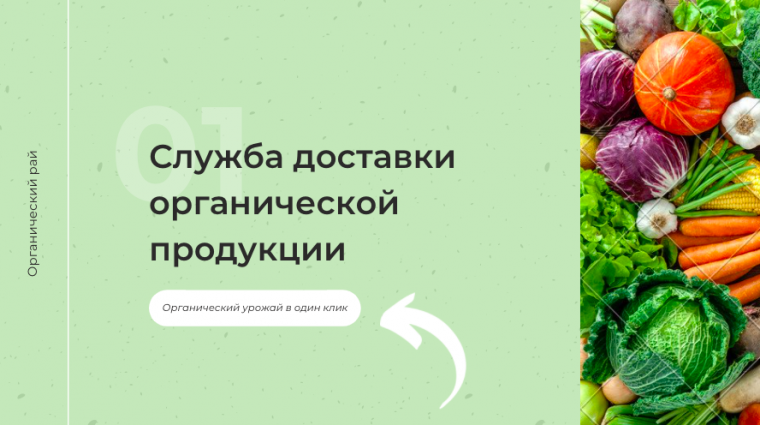
2. Tenor Sans
Еще один шрифт для презентации с очень теплым и доверительным настроением. Его могут смело выбирать начинающие предприниматели, которые не стремятся к большим масштабам, а хотят создать небольшое семейное производство с особым вниманием к деталям. Шрифт для презентации Tenor Sans вызывает ассоциации с семейными рецептами, русскими традициями и ручным производством.
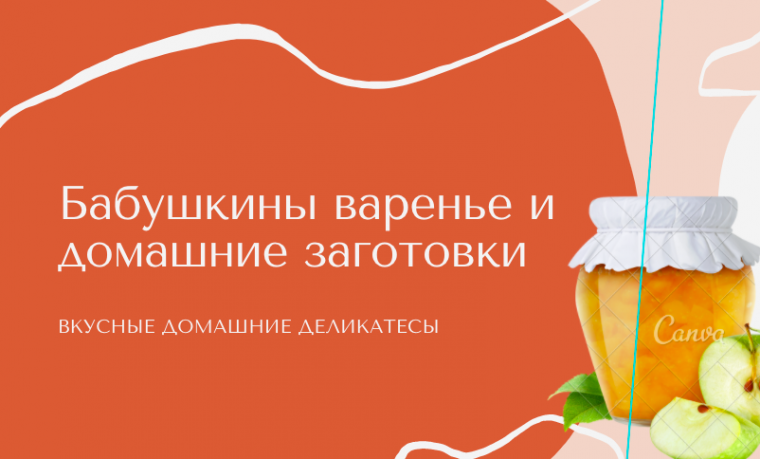
3. HK Grotesk Medium
Этот шрифт для презентации лучше всего смотрится на экране компьютера или планшета. Он хорошо читается за счет простой формы и отсутствия засечек, но при этом выглядит интересно и привлекает внимание. Главное, следить за тем, чтобы шрифт для презентации был нужного размера. HK Grotesk Medium отлично подойдет для материалов инновационных интернет-сервисов и стартапов.
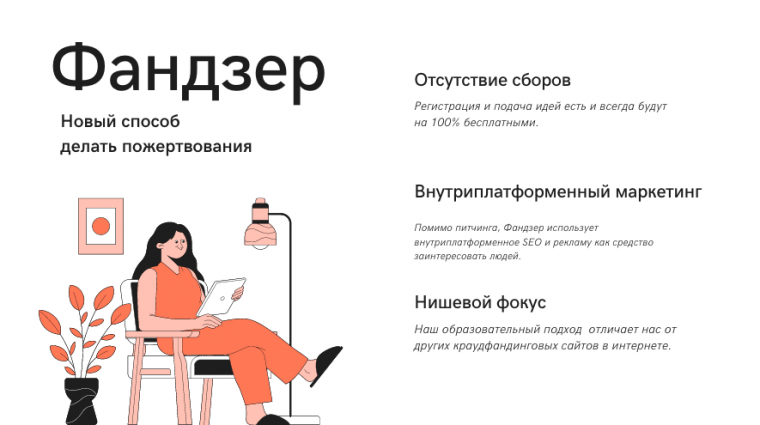
4. Geometria
Geometria — популярный шрифт для презентации, который хорошо знаком даже новичкам. Пропорциональные буквы, простая форма и несколько вариантов начертания позволяют создать читабельные слайды, которые выглядят представительно и сдержанно. Это отличный шрифт для деловой презентации компании.
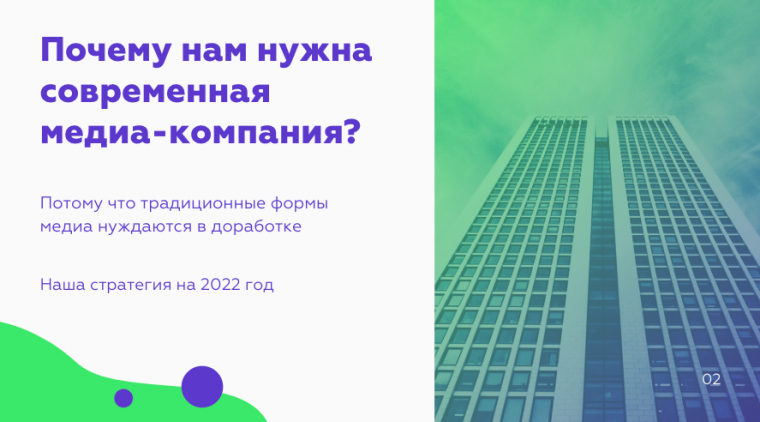
5. Open Sans
Лучшие шрифты для презентации для 2021 года невозможно представить без Open Sans, который занимает ведущее место среди шрифтов для веб-дизайна. Его по умолчанию используют многие интернет-сервисы и приложения. Он универсален и подходит для презентаций на любую тему.
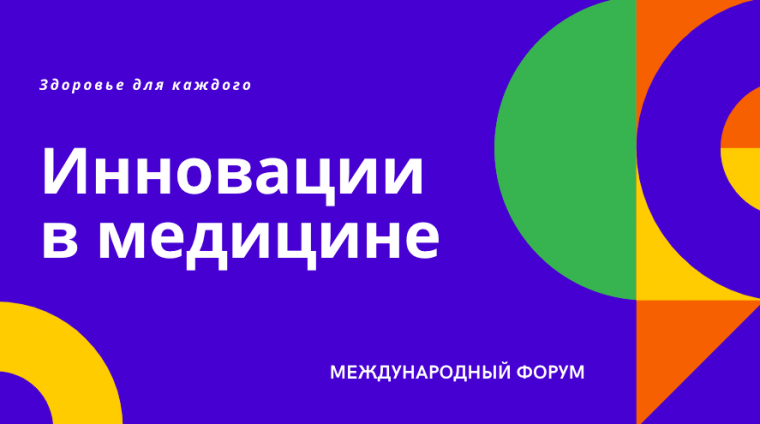
6. Roboto Condensed
Roboto — отличный шрифт для презентации, потому что компания Google разработала его специально для операционной системы Android. По этой причине он отлично смотрится, как на мобильных устройствах, так и на других экранах и проекторах.
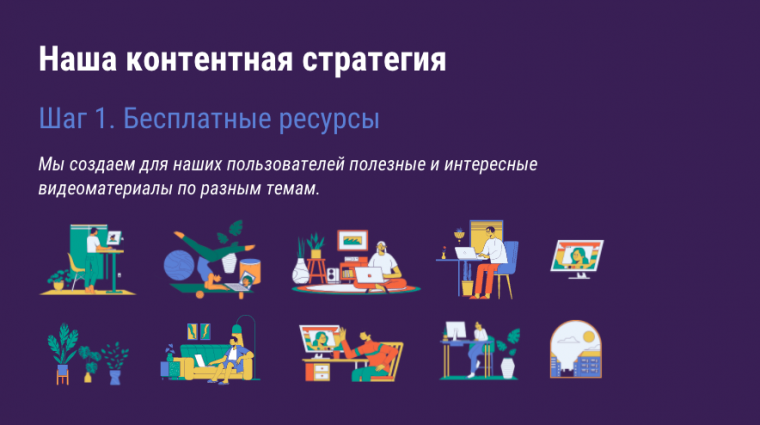
7. Clear Sans Regular
Еще один шрифт для презентации, который отлично читается на любом экране. Clear Sans Regular выглядит представительно и модно одновременно. С его помощью можно удачно оформить материалы, связанные с миром музыки и интернет-сервисами, также он хорошо подойдет для медиа.
8. Fira Sans
Технократичный и ультрасовременный шрифт для презентации Fira Sans лучше всего смотрится на контрастном фоне и хорошо сочетается с кислотными цветами, которые сейчас в моде и ассоциируются с бурным развитием интернет-сервисов. Попробуйте этот шаблон, если готовите материал для интернет-проекта.
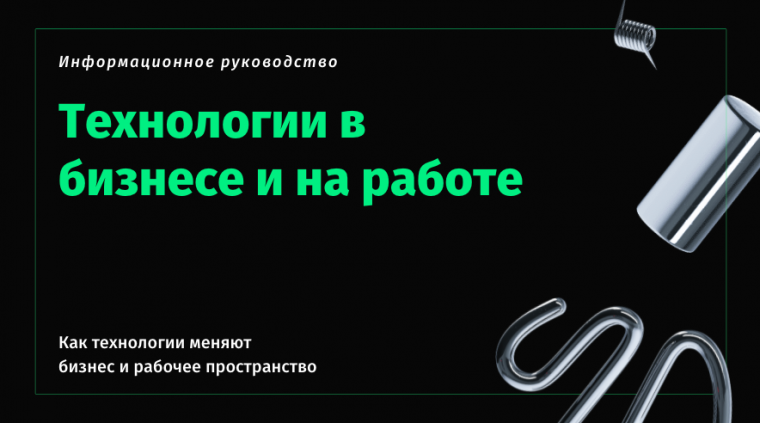
9. Prosto
Еще один отличный шрифт для презентации на тему интернет-технологий. Буквы отличаются открытыми, плавными чертами, а в некоторых из них скругления выполнены оригинальным образом. Отличный шрифт для презентации, если вы хотите выглядеть технологично и современно.
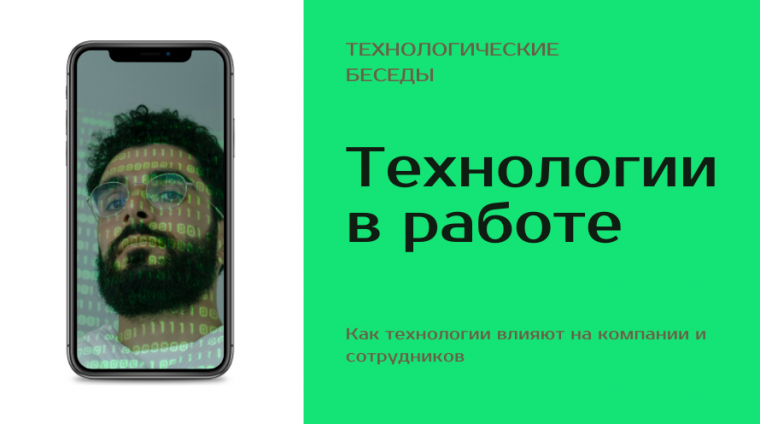
10. Inter
Inter — шрифт для презентации с насыщенными буквами без засечек.
- Отлично подходит для заголовков или оформления объемных текстовых фрагментов;
- хорошо смотрится на контрастном фоне.
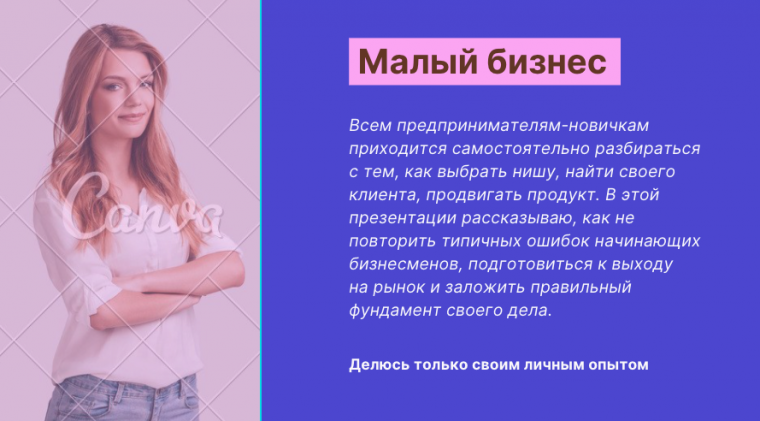
11. Evolventa
Очень элегантный шрифт для презентации с широкими буквами и изящными линиями. Надписи прекрасно читаются и при этом выглядят легкими, что позволяет не перегружать слайды. Evolventa подойдет для таких тем, как архитектура, искусство и культура.
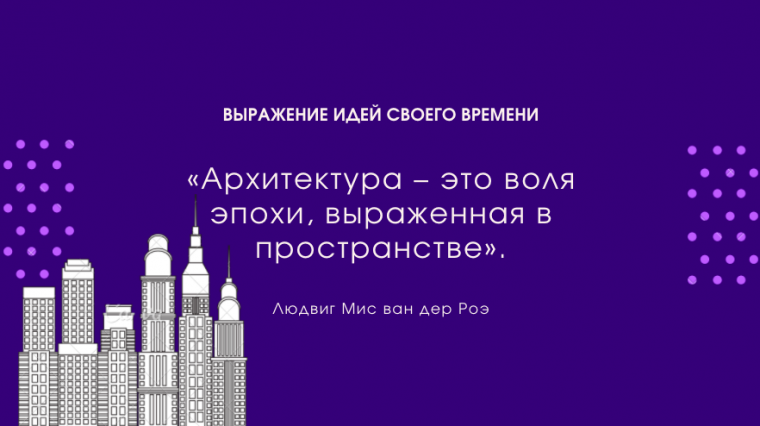
12. Oswald
Oswald — шрифт для презентации с узкими буквами и массивными линиями. Он подойдет для обучающих и информационных материалов. Преимущество этого варианта в том, что даже если вы используете шрифт для презентации небольшого размера, текст будет хорошо заметен.
13. Lora
Шрифты для презентации с засечками выглядят менее сдержанно и официально, поэтому часто используются в сфере моды, красоты и лайфстайла. Текст, оформленный с помощью шрифта Lora, хорошо читается с экрана, в полужирном начертании получаются заметные заголовки, а еще у этого шрифта для презентации красивый курсив.
21. TeX Gyre Adventor
Этот шрифт для презентации идеально подойдет для цифровых слайдом на тему современного искусства. Он отлично читается как в обычном, так и в курсивном и полужирном начертании. С его помощью можно оформить большое количество текста, соблюдая единый стиль.